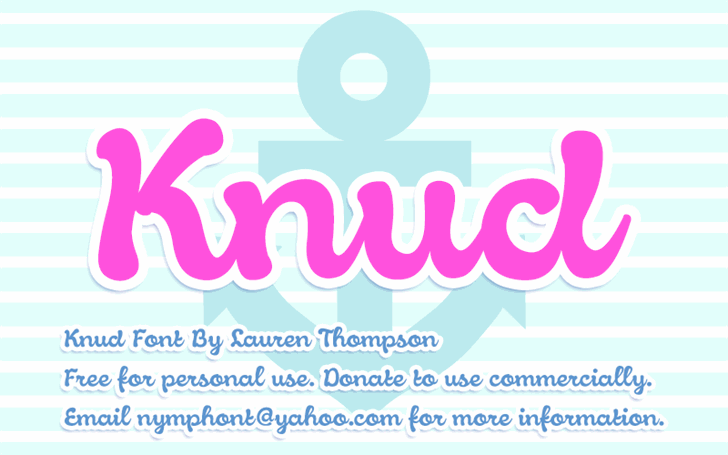
A fonte Knud é uma escolha divertida e ideal para designers que buscam adicionar um toque descontraído a suas criações digitais. Ela foi criada pelo designer Hamilton, trazendo uma mistura única de linhas curvas suaves com traços robustos, dando ao texto um ar playfull sem perder sua legibilidade. Embora seja classificada como um fonte casual ou leve, Knud se adapta perfeitamente a diversas aplicações. Desde design gráfico até editoração online, ela oferece uma variedade de opções para tornar qualquer projeto mais interessante e criativo. Se você está procurando por algo que dê vida a suas mensagens de email ou redes sociais com um toque divertido sem perder o essencial da legibilidade, Knud é definitivamente uma fonte a ser considerada.